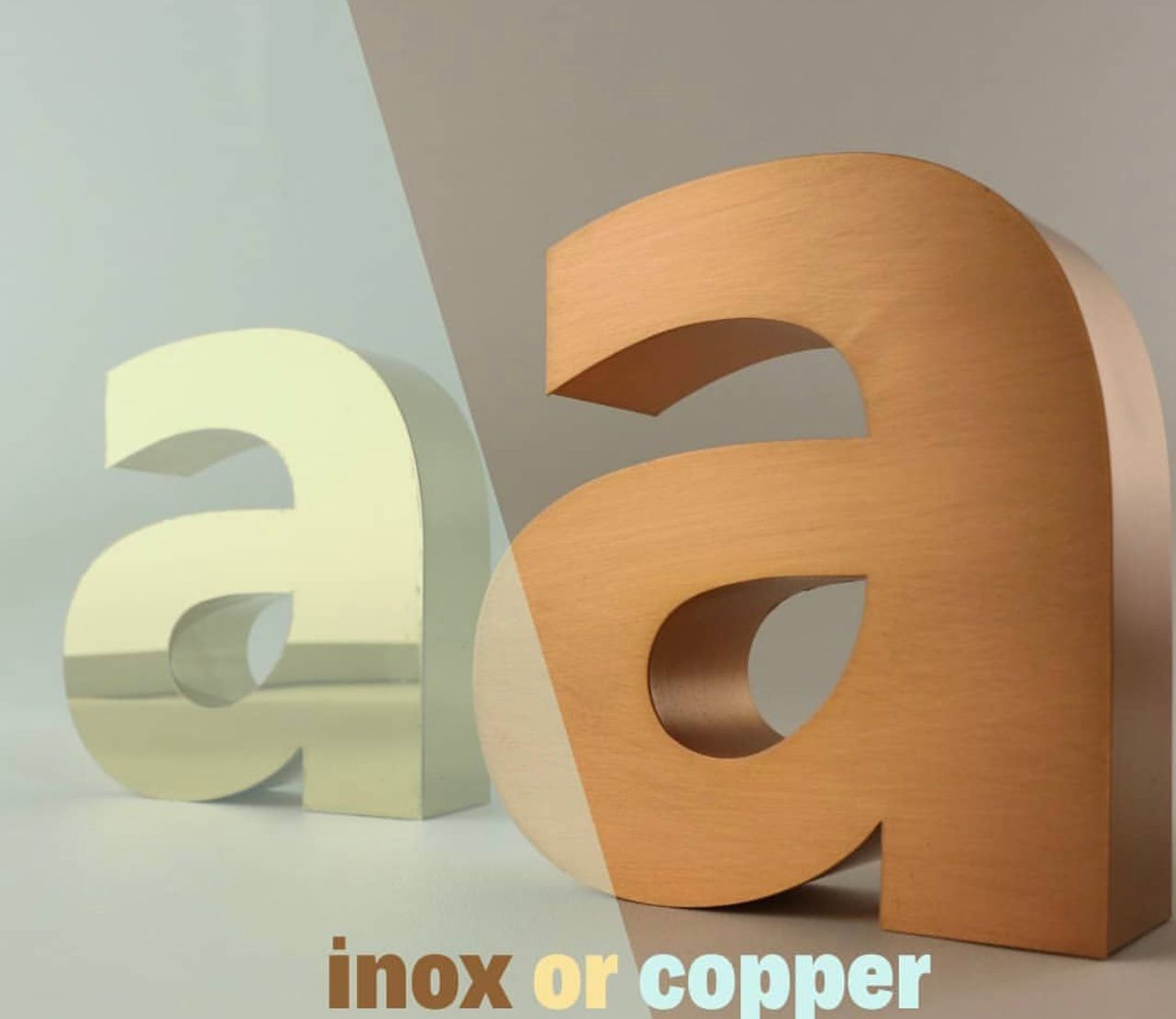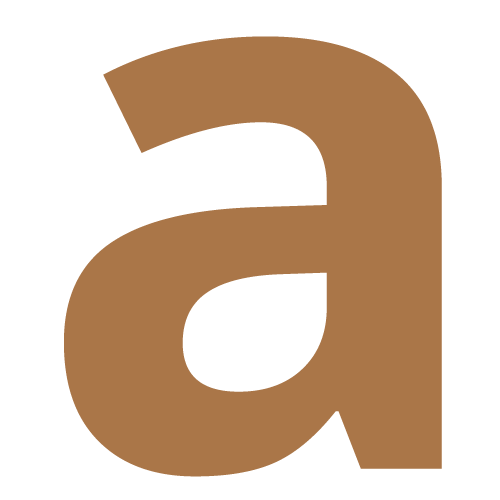
What the font bulamadı
Daytona Pro Condensed Fat WhatFontIs.com
Evet hocam bende bulamadım belki aşina olanlar vardır diye açtım
Ona benzemiyor maalesef
Montserrat tarzı ama tam montserrat değil
Hocam belirli sitelerden bakıyoruz arkadaşlar yukarıda belirtmiş ben de çoğunlukla onları kullanıyorum ama daimi çözüm olmuyor.
En iyisi @RifatOzkan; hocamın dediği gibi transparan hale getirmek, sonucu iyileştiriyor.
Onun dışında meşhur font sitelerinden -googlefonts, dafont vb...- yalnızca a metnini yazıp benzerini yakalamak benim kullandığım bir yöntem.
open sans bu,
a'nın ortasındaki boşluktan anlayabilirsiniz
@patrick2dev; hocamın gözüne güvenerek bir baktım, gerçekten o sanırım. Yalnızca kuyruk kısmında bir ufak boşluk durum var, o da muhtemelen vektöreldir. Program önümdeydi, Open Sans böyle;
gözüme en yakın gelen bu oldu ama ya font farklı yada uçlarına manuel oynama yapılmış